Desde el Reino Unido nos llegan estas ilustraciones tipográficas de la mano de Robert Missen. Sin duda un estilo muy peculiar y atractivo que no deja indiferente, aunque igual me recuerda demasiado al trabajo de Si Scott ( o viceversa).
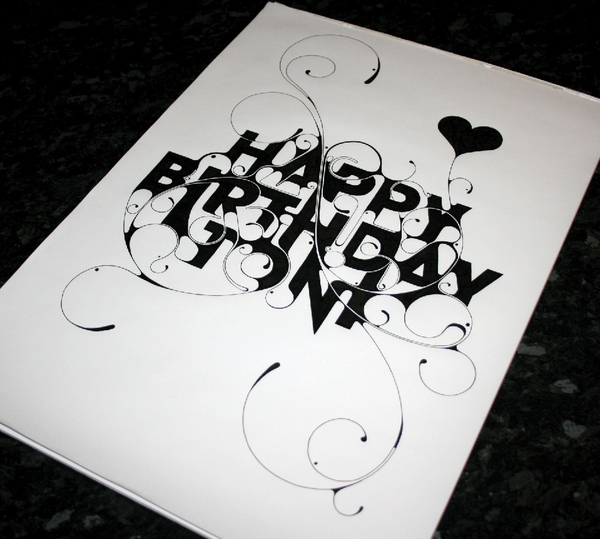
Desde el Reino Unido nos llegan estas ilustraciones tipográficas de la mano de Robert Missen. Sin duda un estilo muy peculiar y atractivo que no deja indiferente, aunque igual me recuerda demasiado al trabajo de Si Scott ( o viceversa).